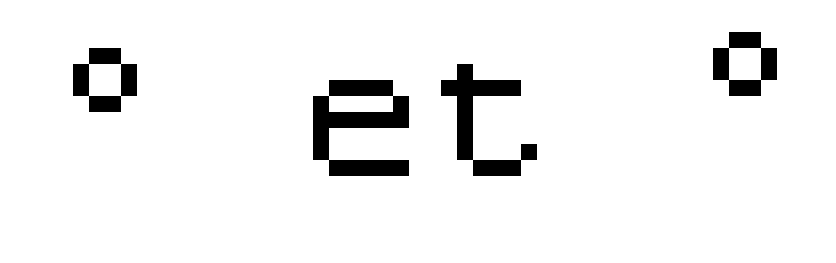
Jacques André a écrit :
Le 26 août 2010 à 15:25, Luc Bentz (listes) a écrit :Le 26/08/2010 15:21, Nicolas Larderet a écrit :- le degré après le n pour abréger numéro est-il acceptable, en sachant que je n'ai pas accès aux exposants ?Pourquoi pas lui recommander d'utiliser plutôt le signe ordinal masculin (exposant o) º : Unicode+00BA (HTML:º º) que sur mon Mac j'obtiens en faisant "alt u" (u comme up) => º et qui doit bien se trouver sur Windows & Co. C'est quand même plus joli : comparer º et ° (ce dernier=degré).-- Jacques ANDRÉ
Il est vrai qu'en comparant à 1600% sur photoshop, la différence saute aux yeux ;)